教科書体
教科書体(きょうかしょたい)は「小学校学習指導要領」の「学年別漢字配当表」に載っている漢字書体に従って作られた書体で、小学校の教科書で使われています(中学校以降の教科書では明朝体が使われています)。手書きの楷書体に近いデザインになっています。
教科書体一覧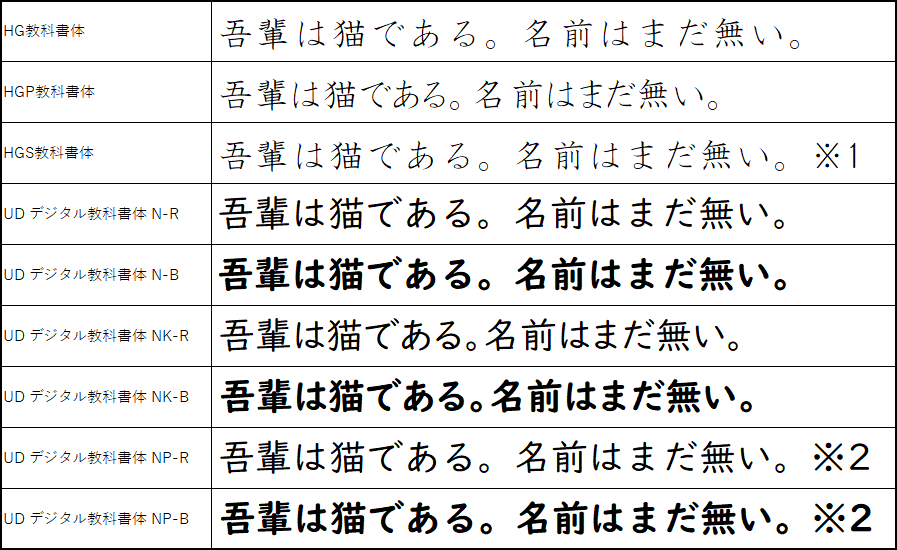
※1=半角文字だけプロポーショナルフォント。※2=かなと英数がプロポーショナルフォント。
HG書体
HG教科書体(等幅フォント)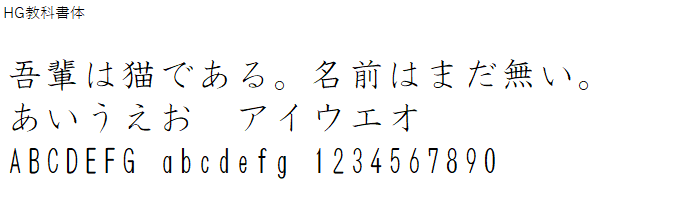
HGP教科書体(プロポーショナルフォント)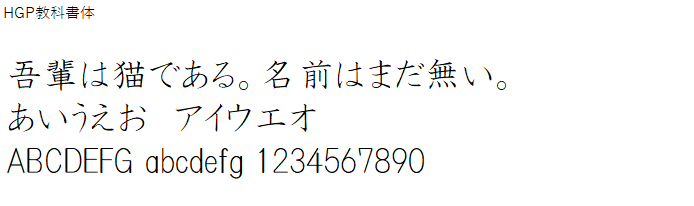
HGS教科書体※半角文字だけプロポーショナルフォント。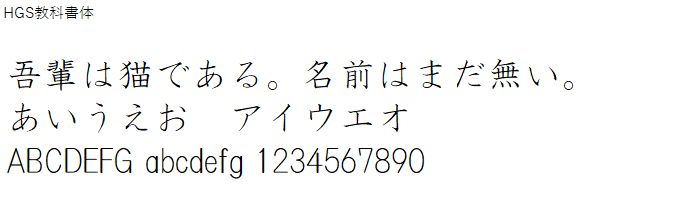
ユニバーサルデザイン書体
ユニバーサルデザイン書体は、可読性・視認性・判読性が高くなるようにデザインされたフォント。UDと略す。フォント名末尾の「R」「B」は文字の太さの違いを表す。
UD デジタル教科書体 N-R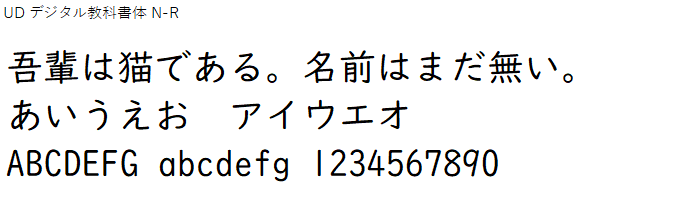
UD デジタル教科書体 N-B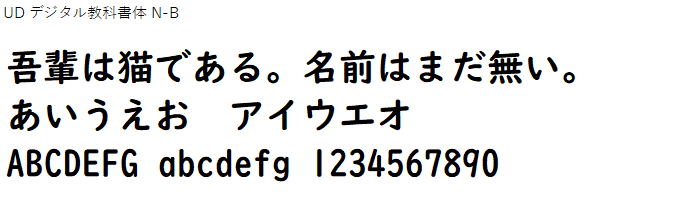
UD デジタル教科書体 NK-R※かなと英数がプロポーショナルフォント。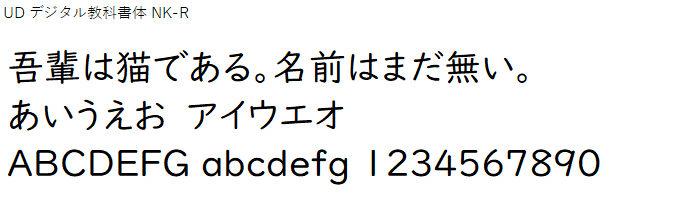
UD デジタル教科書体 NK-B※かなと英数がプロポーショナルフォント。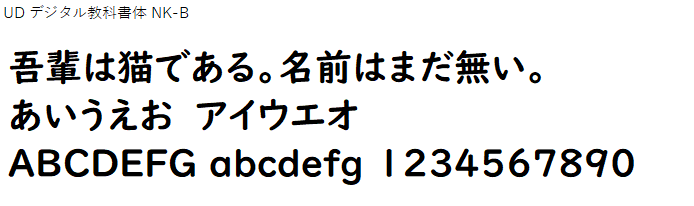
UD デジタル教科書体 NP-R※英数のみプロポーショナルフォント。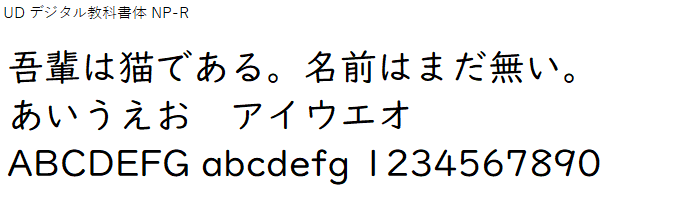
UD デジタル教科書体 NP-B※英数のみプロポーショナルフォント。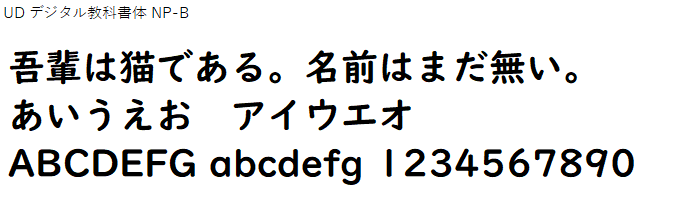